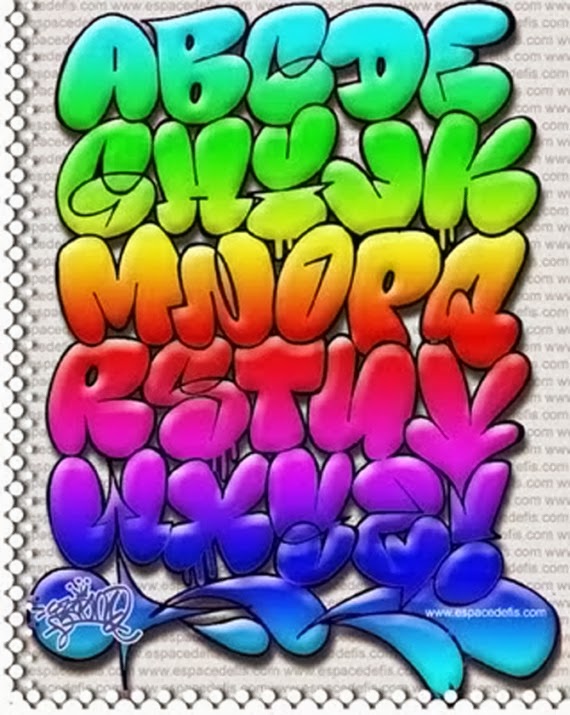
Этот граффити-шрифт отличается непринужденным и забавным дизайном букв, который напоминает мультяшный стиль. Это делает его отличным выбором для создания названий и заголовков для проектов, связанных с детьми. Шрифт поставляется с заглавными буквами с дополнительной версией контура.
Этот шрифт идеально подходит для создания современной рукописной типографики с элементами граффити.